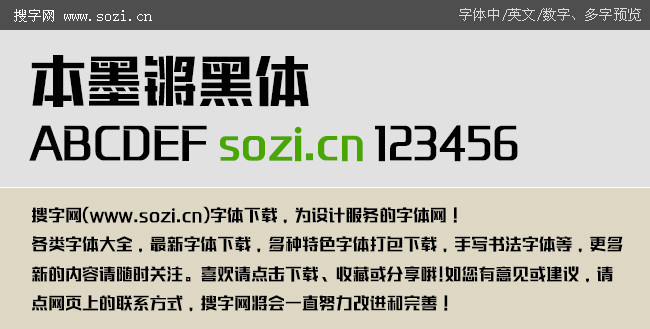
本墨鏘黑體
搜字網(wǎng)提供一款本墨鏘黑體中文藝術(shù)字體下載,該字體擁有較強(qiáng)的視覺(jué)沖擊力,而且筆畫(huà)工整、大氣,特別是收筆、橫、折等均是像有方塊組成的,看上去十分地蒼勁有力。適用于書(shū)籍設(shè)計(jì)、報(bào)紙標(biāo)題、畫(huà)冊(cè)設(shè)計(jì),網(wǎng)頁(yè)設(shè)計(jì)等應(yīng)用。